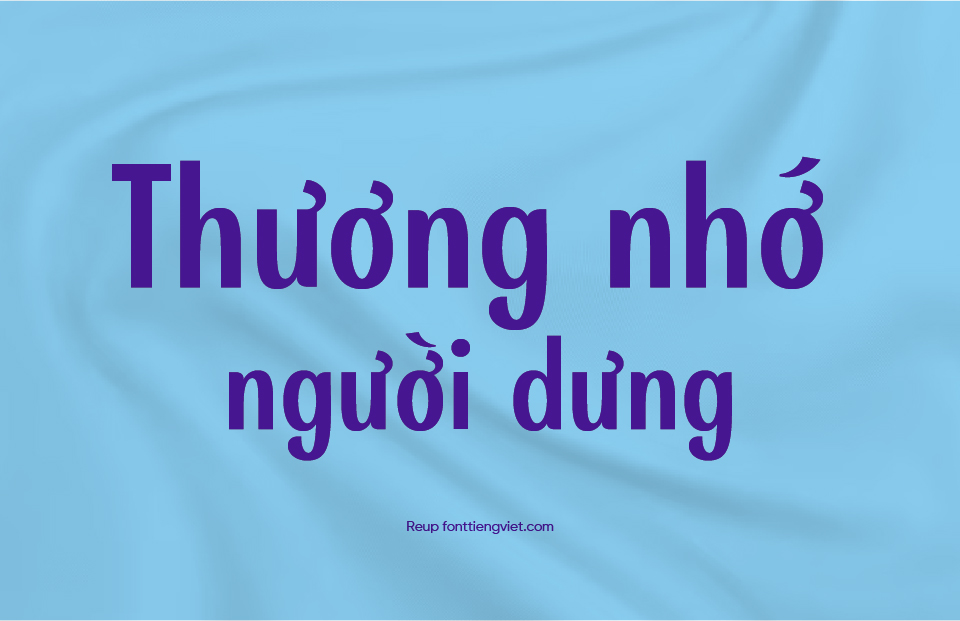
Font tiếng Việt Finesse
Giới thiệu về bộ Font tiếng Việt Finesse
Trong thế giới đồ họa hiện đại, việc lựa chọn một Font Miễn Phí chất lượng luôn là ưu tiên hàng đầu của các bạn học sinh và giáo viên. Font tiếng Việt Finesse nổi lên như một giải pháp hoàn hảo nhờ sự kết hợp tinh tế giữa nét chữ thanh mảnh và cấu trúc hiện đại. Đây là bộ font được thiết kế với phong cách tối giản nhưng không kém phần sang trọng, rất phù hợp cho các bài thuyết trình, báo cáo học tập hay các dự án thiết kế sáng tạo tại trường học. Việc sử dụng Font tiếng Việt Finesse giúp nội dung trở nên dễ đọc, chuyên nghiệp và thu hút thị giác người xem ngay từ cái nhìn đầu tiên.
Ưu điểm nổi bật của Font tiếng Việt Finesse
Khả năng hiển thị đa dạng và chuẩn xác
Điểm mạnh nhất của Font tiếng Việt Finesse chính là khả năng hỗ trợ đầy đủ bảng mã tiếng Việt. Bạn sẽ không còn lo lắng về lỗi font hay các ký tự đặc biệt bị biến dạng khi soạn thảo văn bản. Với các đường nét được trau chuốt kỹ lưỡng, bộ font này mang lại cảm giác thanh thoát, giúp giảm bớt sự khô khan trong các tài liệu giáo khoa. Ngoài ra, Finesse còn có nhiều định dạng từ mỏng đến đậm, cho phép người dùng linh hoạt tùy chỉnh cho tiêu đề hoặc nội dung văn bản tùy theo mục đích sử dụng cụ thể.
Ứng dụng thực tế trong môi trường giáo dục
Font tiếng Việt Finesse thường được các bạn học sinh ưu tiên dùng để làm poster sự kiện, thiết kế bìa tiểu luận hoặc trang trí slide PowerPoint. Sự hiện đại của font chữ này giúp các bạn trẻ thể hiện được cá tính sáng tạo mà vẫn giữ được chuẩn mực cần thiết. Đối với thầy cô, đây là công cụ hữu ích để làm mới các bộ học liệu, giúp bài giảng trở nên sinh động và hiện đại hơn so với các bộ font truyền thống đã quá quen thuộc.